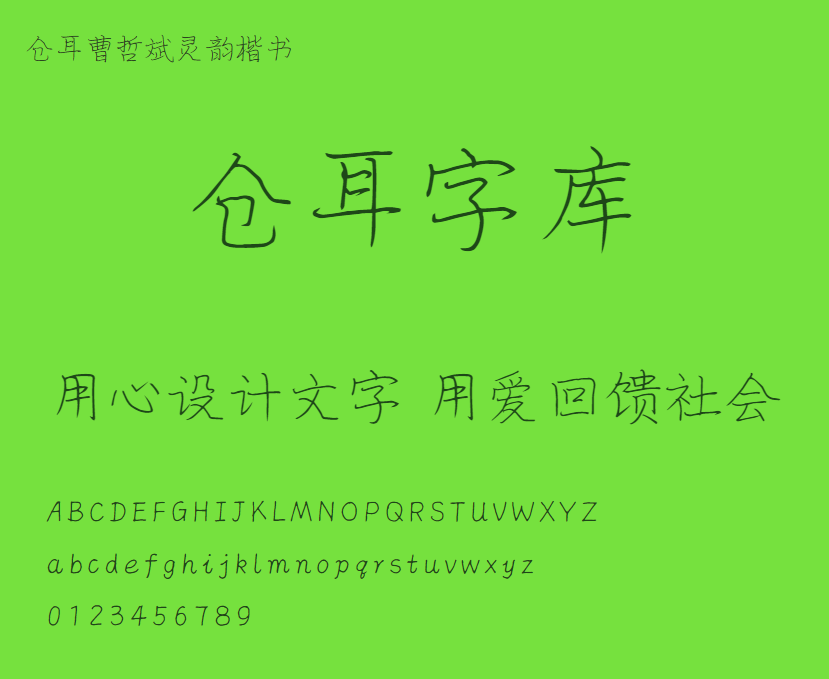
仓耳曹哲斌灵韵楷书加粗
仓耳曹哲斌灵韵楷书加粗,这款字体结构工整、笔画清晰,兼顾美观与易读性,适用于标题、正文、海报、包装、LOGO 等多种场景。字形优雅稳定,风格百搭耐看,适配日常排版与创意设计,让文字呈现更舒适、更具质感。仓耳曹哲斌灵韵楷书加粗一笔一画,皆是细节,以均衡的比例、流畅的线条打造舒适视觉体验,字形端正大气,风格简约现代。无论是商业设计、品牌宣传还是日常排版,都能轻松驾驭,让文字更有格调与力量。仓耳曹哲斌灵韵楷书加粗字体下载。